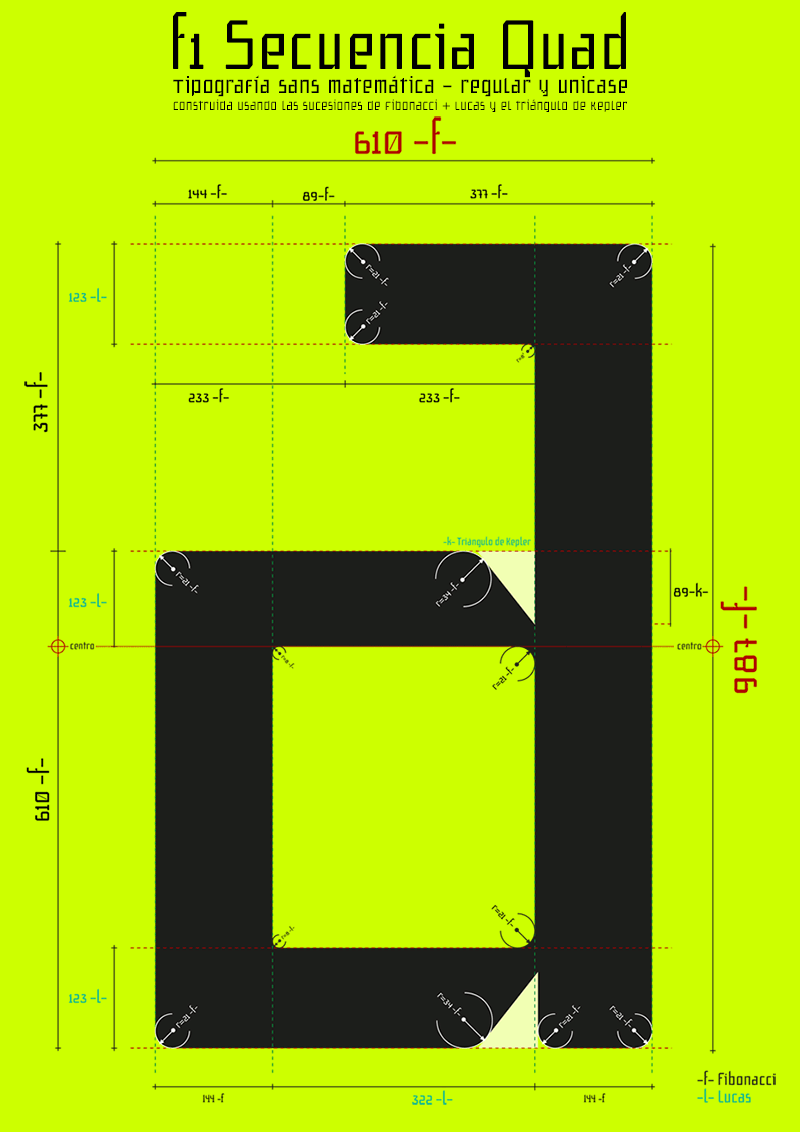
A mediados del año 2012 comencé con un proyecto tipográfico al que he llamado Secuencia, la base de esta idea es la construcción geométrica de letras siguiendo una relación de proporciones basada en la Sucesión de Fibonacci y la de Lucas, también uso algún número de Perrin o números de Tribonacci, pero son las menos, aunque todas estas sucesiones comparten la misma propiedad, al dividir un número de la sucesión por su inmediato anterior nos da un número que se acerca al número áureo.
Tipografía áurea φ
Estilo: Geométrica, Sans serif
Proporción: Regular
Con el triángulo de Kepler he horadado los nudos de las astas o matado algún vértice como en la S mayúscula para dar más ligereza en la lectura y crear movimiento propio a cada caracter, la proporción de los lados de un triángulo de Kepler tiene que ver con el número áureo. En si misma, cada letra es un ejercicio de proporciones perfectas, un icono áureo punto de partida de diseños tipográficos minimalistas o complejos, base de dibujo para composiciones de posters o carteles.
Durante el dibujado de las letras me he encontrado con cifras resultantes de otras secuencias, curiosas, no buscadas, por ejemplo en la medida resultante en las contraformas y ojos o el centro natural de las letras que coincide con la parte inferior de la barra media 377 pt + 123 pt. Cabe resaltar también que tanto la métrica de los caracteres así como el tracking, el hinting y el interletraje los he definido con números de las secuencias, consiguiendo así total armonía entre las formas y en la lectura y escritura de párrafos.
Sucesión de Fibonacci: 0, 1, 2, 3, 5, 8, 13, 21, 34, 55, 89, 144, 233, 377, 610, 987, 1597, 2584…
Sucesión de Lucas: 2, 1, 3, 4, 7, 11, 18, 29, 47, 76, 123, 199, 322, 521, 843, 1364, 2207…
Números de Perrin (primos): 3, 2, 5, 7, 10, 12, 17, 22, 29, 39, 51, 68, 90, 119, 158, 209, 277, 367, 486…
Números de Tribonacci: 1, 2, 4, 7, 13, 24, 44, 81, 149, 274, 504, 927, 1705, 3136…
Comienzo esta edición de fuentes gratuitas con la f1 Secuencia Quad en la versión Regular y Unicase, próximamente mostraré las versiones Slab Serif e Itálica. Sin olvidarme de la versión Rounded de esta familia de tipos, donde las curvas toman protagonismo, podéis ver en acción la tipografía f1 Secuencia Rounded en versiones Regular y Bold en los títulos de los artículos y Widgets de esta web, actualmente la familia f1 Secuencia Rounded la componen la versión Regular, Bold, Italic, Slab Serif regular e itálica y la versión Unicase.
Toda esta familia corresponde a la primera serie de fórmulas de proporciones áureas combinadas (f1).
El uso práctico de esta fórmula se puede ver en el poster constructivo de la letra ‘a’ minúscula, observar las proporciones que inscriben la letra, 987×610 pt, dos números correlativos de la sucesión de Fibonacci que conforman lo que se llama un rectángulo áureo.
A partir de esta rejilla comienzo la construcción de las letras minúsculas de caja baja, las astas verticales de un grosor de 144 pt y las transversales, diagonales o barras con 123 pt (Secuencia de Lucas).
El tamaño del hombro de la letra es de 377 pt y la altura del anillo 610 pt, finalizo la construcción de la letra suavizando los vértices externos e internos con curvas de radios pertenecientes a la secuencia de fibonacci, por fin recorto los nudos de unión de las astas y barras con un triángulo de Kepler de 89 pt de altura, este recorte favorece la lectura de la letra en pequeños tamaños, con el recorte inferior creo una especie de espolón cuadrado.
Con este método he construido todo el alfabeto, en el caso de las minúsculas de caja alta la altura de los ascendentes es de 1597 pt y en el caso de los descendentes es de -377 pt. Para las mayúsculas la altura es de 1364 pt (Sucesión de Lucas).
Por último toda la definición de espacio entre caracteres y kerning (232 pares principales y 2269 heredados) así como como el espaciado de palabras (Tracking) está definido con números de las secuencias matemáticas.
La tipografía Secuencia dispone de un juego de caracteres de 468 caracteres (Extended Latin) con soporte para cualquier idioma europeo o centro europeo con funciones Open Type: Números en versalita, fracciones, ligaduras estándar y discrecionales, letras alternativas, etc. También incluyo una versión Unicase completa y la versión regular como webfont con hojas de estilo de prueba para el uso en páginas web, esta fuente por su construcción simple y geométrica tiene un comportamiento de lectura excelente en sus versiones webfont a pequeño tamaño.